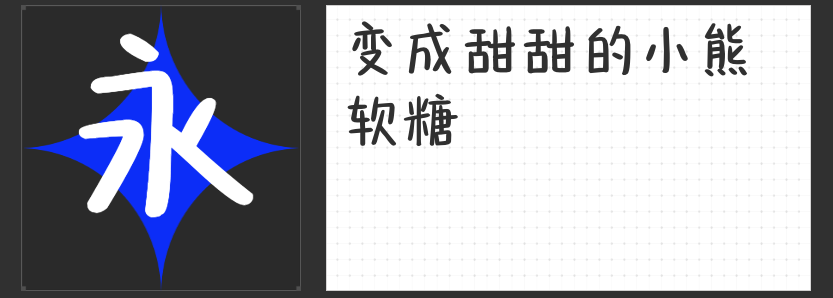
四款匠心字体推荐:为LOGO设计注入独特灵魂
在LOGO设计中,字体不仅是信息载体,更是品牌性格的视觉化表达。一款合适的字体能瞬间传递品牌气质,成为记忆点与辨识度的核心。今天,我们精选四款风格鲜明、适用于LOGO设计的非免费字体,它们以独特的笔触与结构,为品牌注入独一无二的灵魂。
一、造字侠侠义简繁
造字侠侠义简繁以“狂放”为骨,以“圆转”为魂,用流畅的弧线替代生硬的折角,勾、挑、牵丝的笔意如行云流水,既有书法的洒脱不羁,又兼具现代设计的秩序感。其端正平稳的架构下暗藏流动韵律,适合文化、艺术、运动类品牌,传递大气磅礴的品牌格局,同时以细节处的呼应强化LOGO的整体性。
二、励字志向黑简 超粗
励字志向黑简 超粗以“圆体与黑体融合”为突破点,在粗壮有力的笔画中加入外圆角设计,既保留黑体的稳重,又注入圆体的灵动。其字面充实、结构均衡的特点,尤其适配屏显环境,无论是科技、金融还是制造业品牌,都能通过这款字体传递专业感与现代感,同时圆角的细节处理让LOGO更具亲和力。
三、字圈也字可爱小熊体
以小熊为灵感的字圈也字可爱小熊体,从字形到性格皆充满童趣。横斜竖直、左低右高的结构打破传统平衡,折笔处的钝角与直角交替出现,棱角时而圆润时而尖锐,仿佛小熊的调皮与自信。这款字体适合儿童品牌、文创IP或创意工作室,其“不在乎他人看法”的个性,能为LOGO注入独特的生命力,成为品牌与受众的情感纽带。
四、励字憨憨简
励字憨憨简以“圆弧”为基调,笔画饱满如充气玩具,字形圆润却不失结构感,充满童真与活力。其装饰性极强的设计,适合餐饮、娱乐或年轻化品牌,通过圆弧的视觉语言传递轻松愉悦的品牌氛围,让LOGO在第一时间抓住眼球,同时圆润的笔画让品牌显得亲切可靠。
LOGO设计是品牌与世界的第一次对话,而字体则是这场对话的“声音”。这四款字体能以独特的笔触与结构,为品牌LOGO注入灵魂。选择一款与品牌气质高度契合的字体,便是设计成功的第一步。